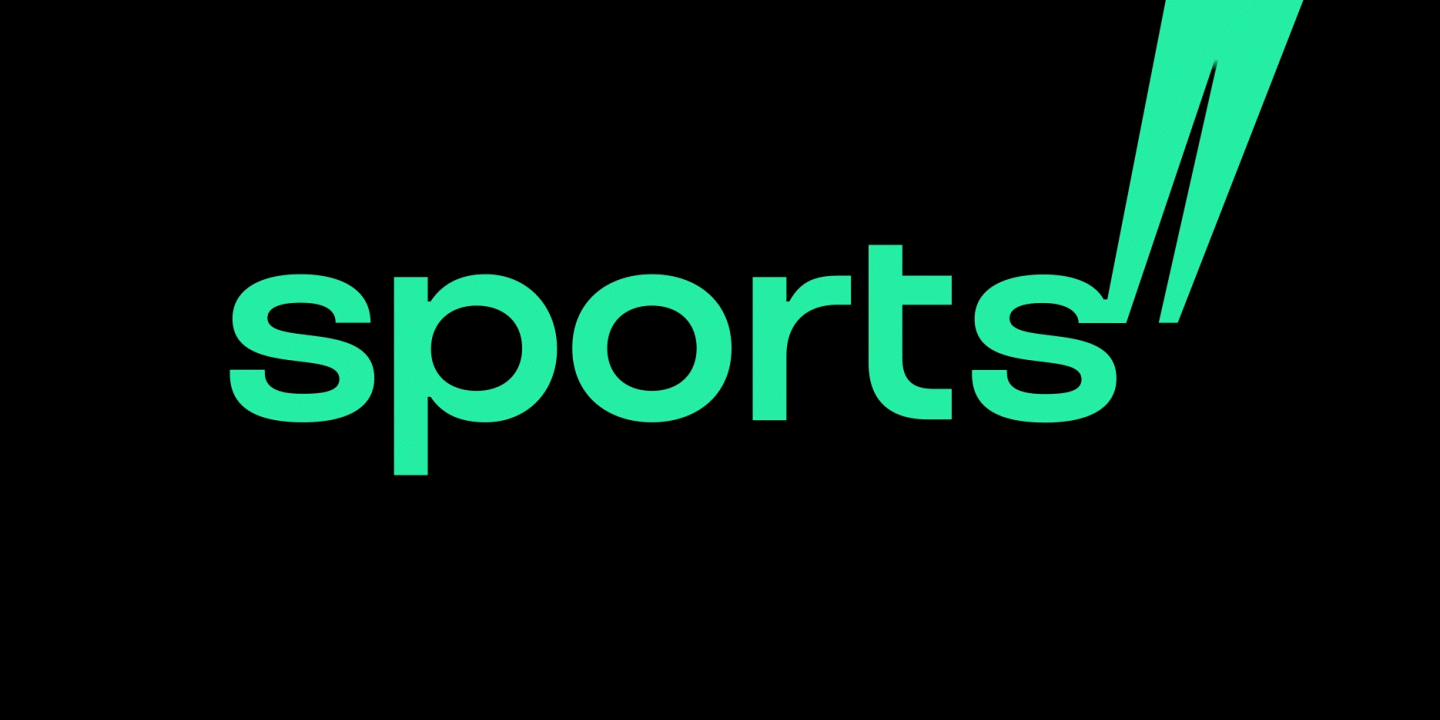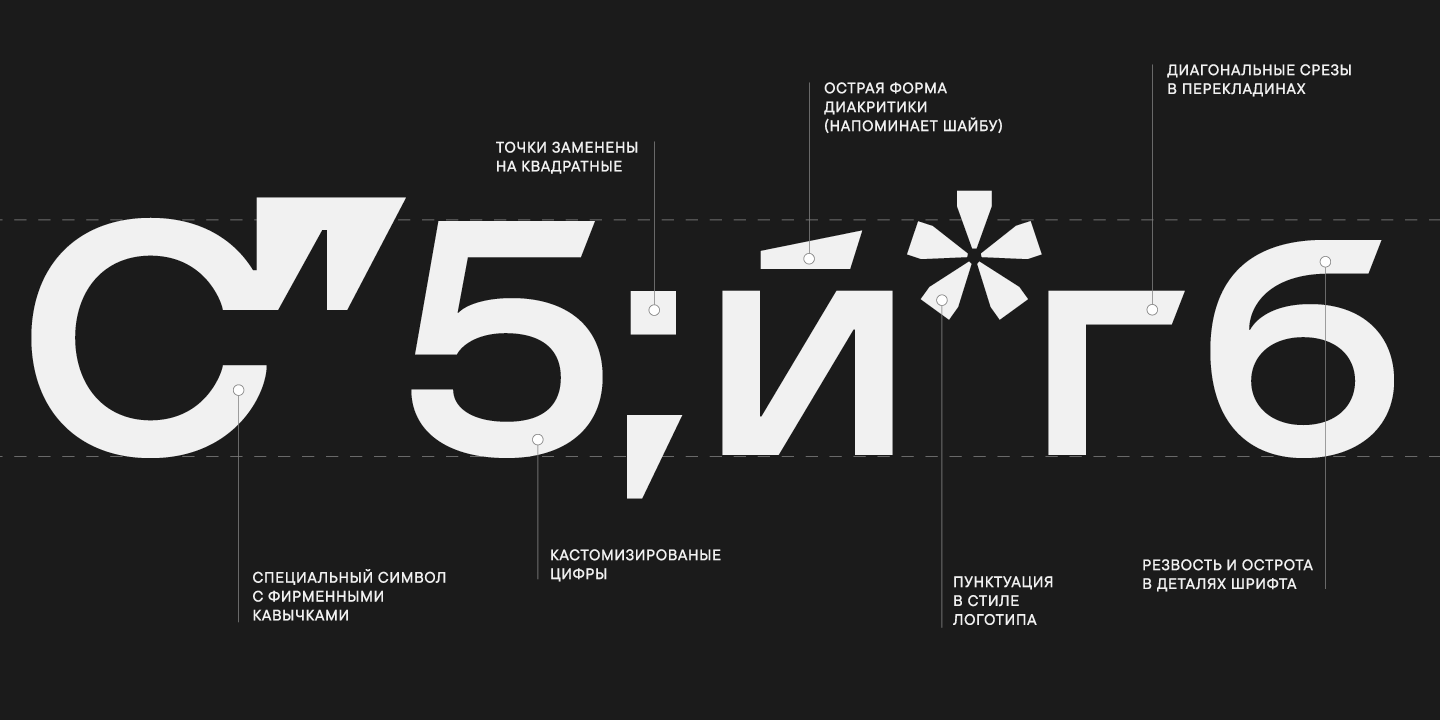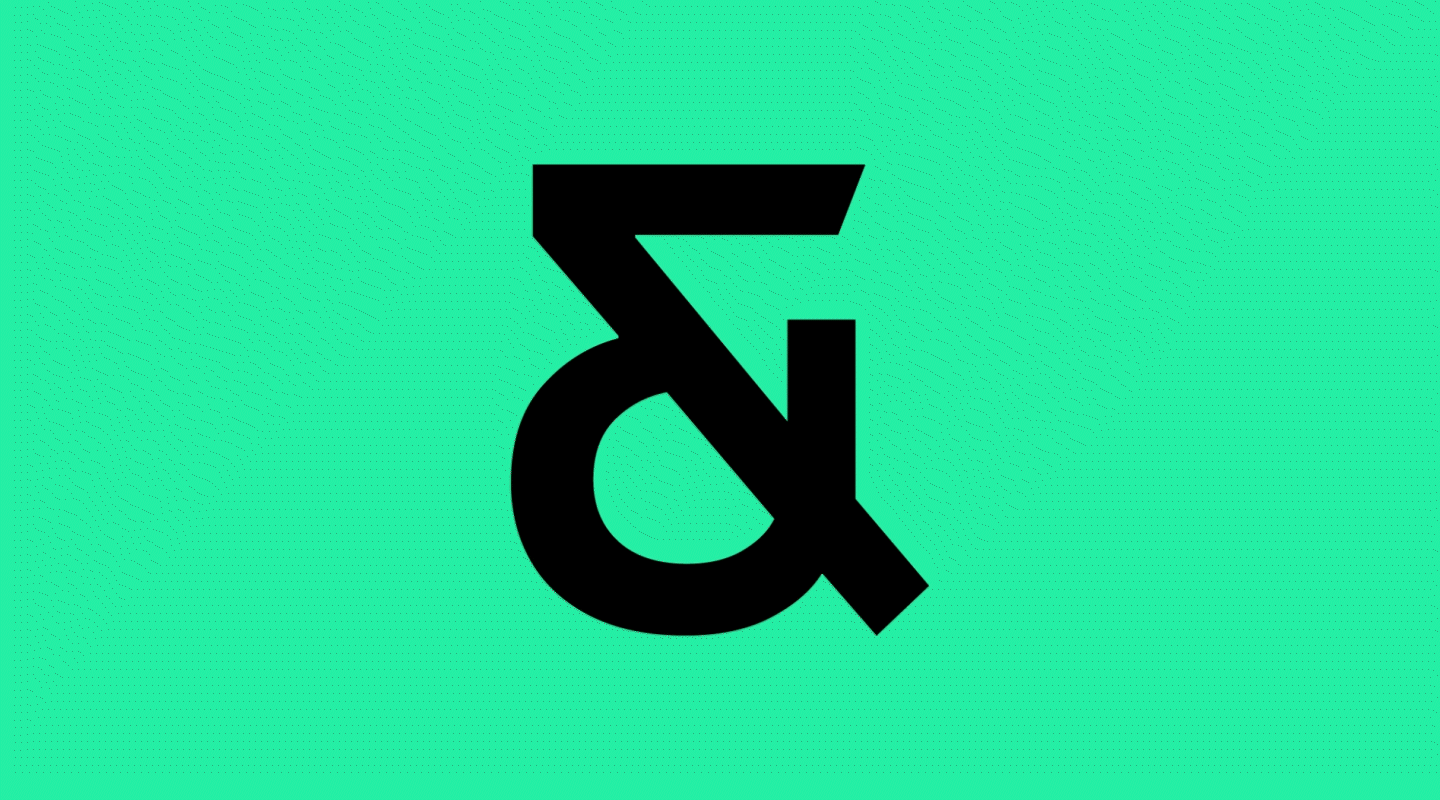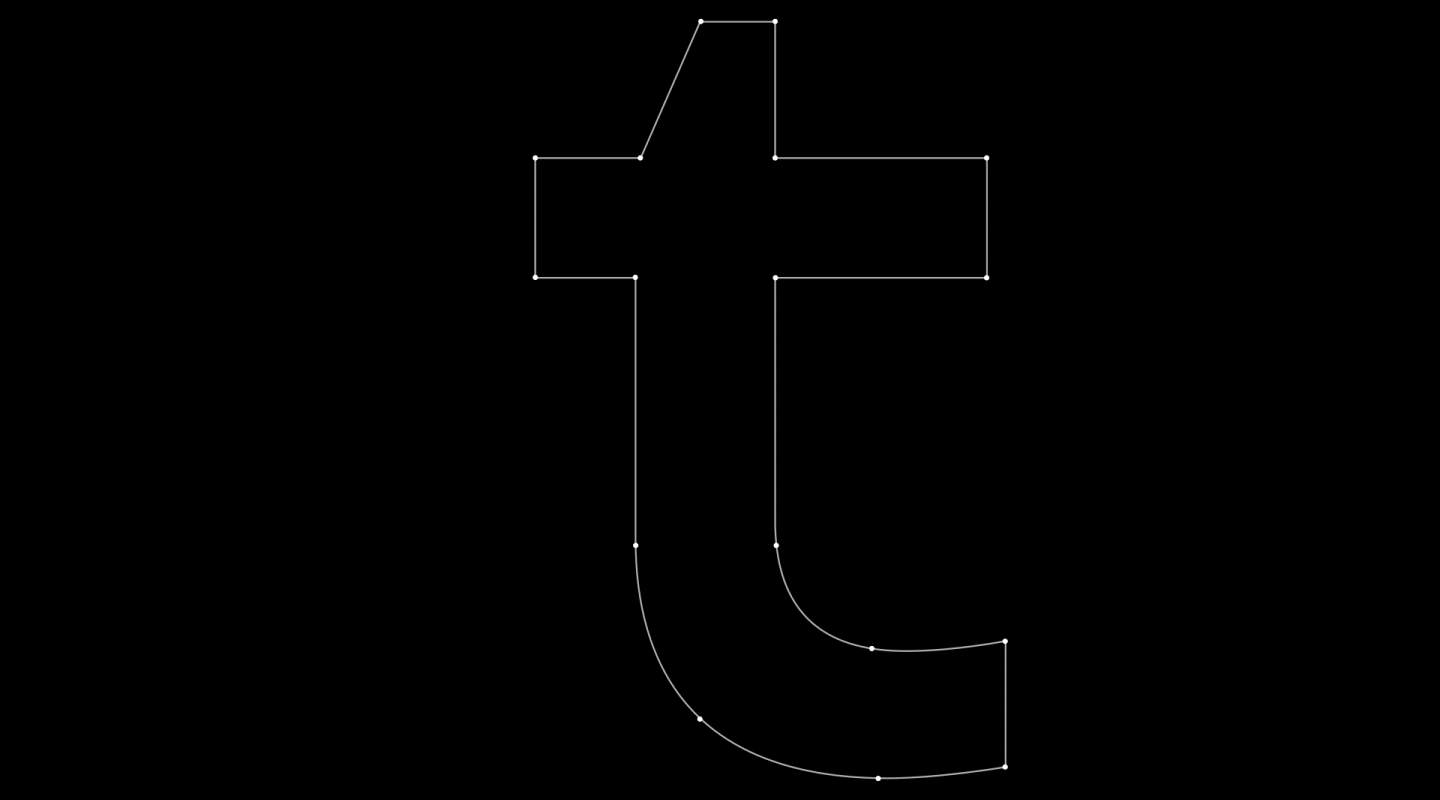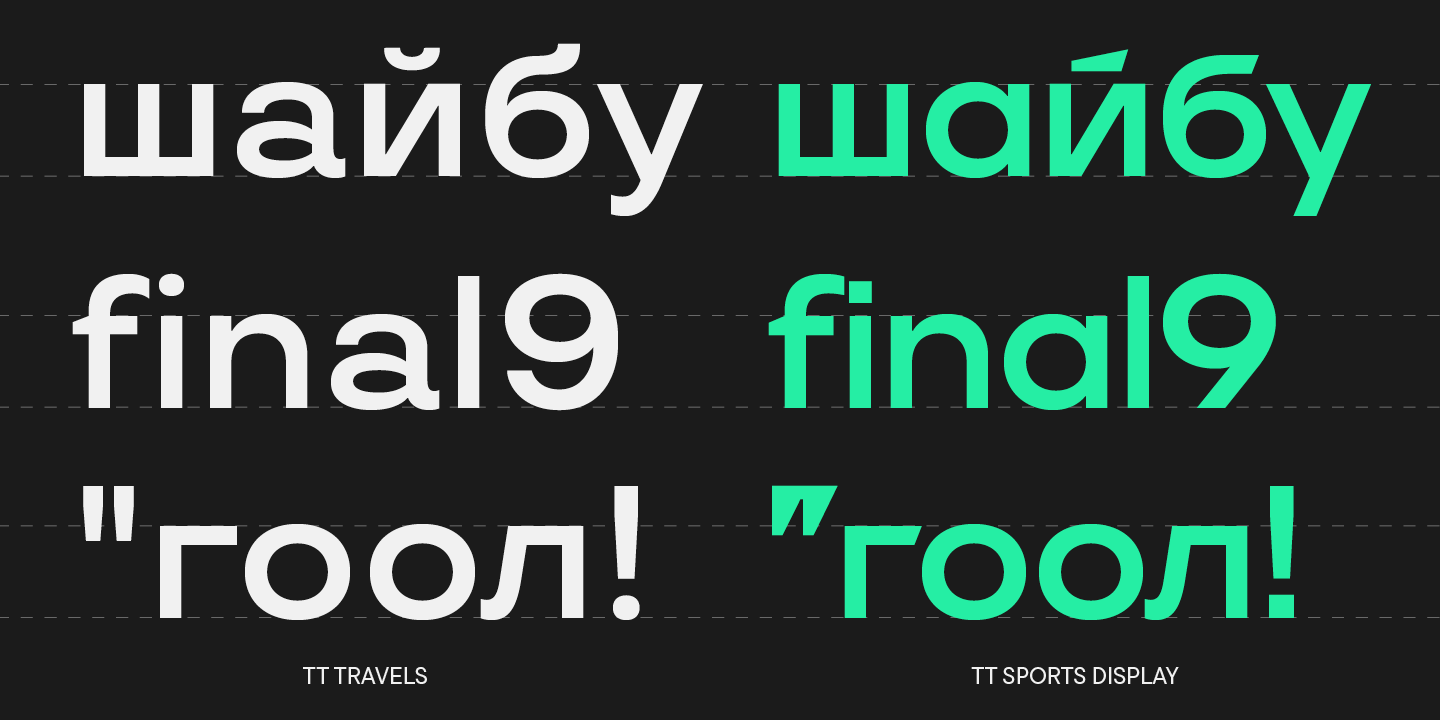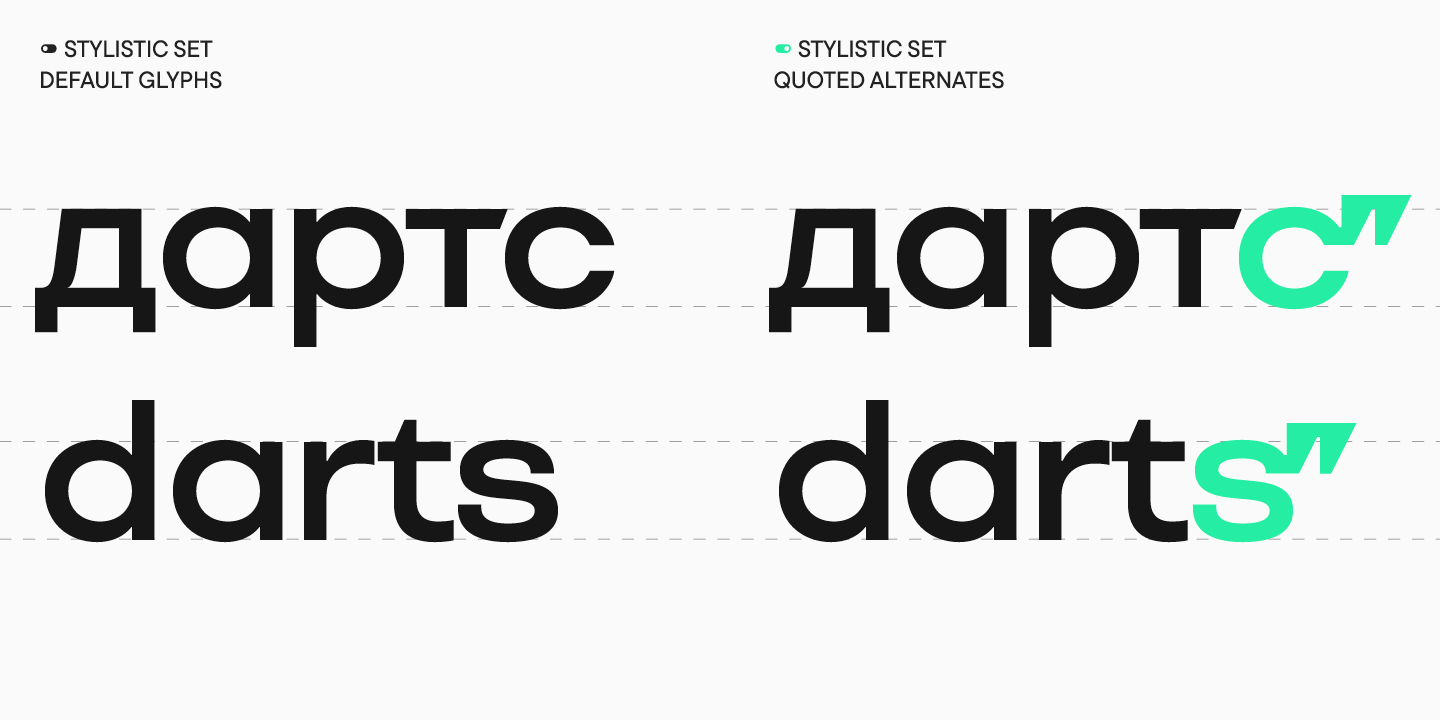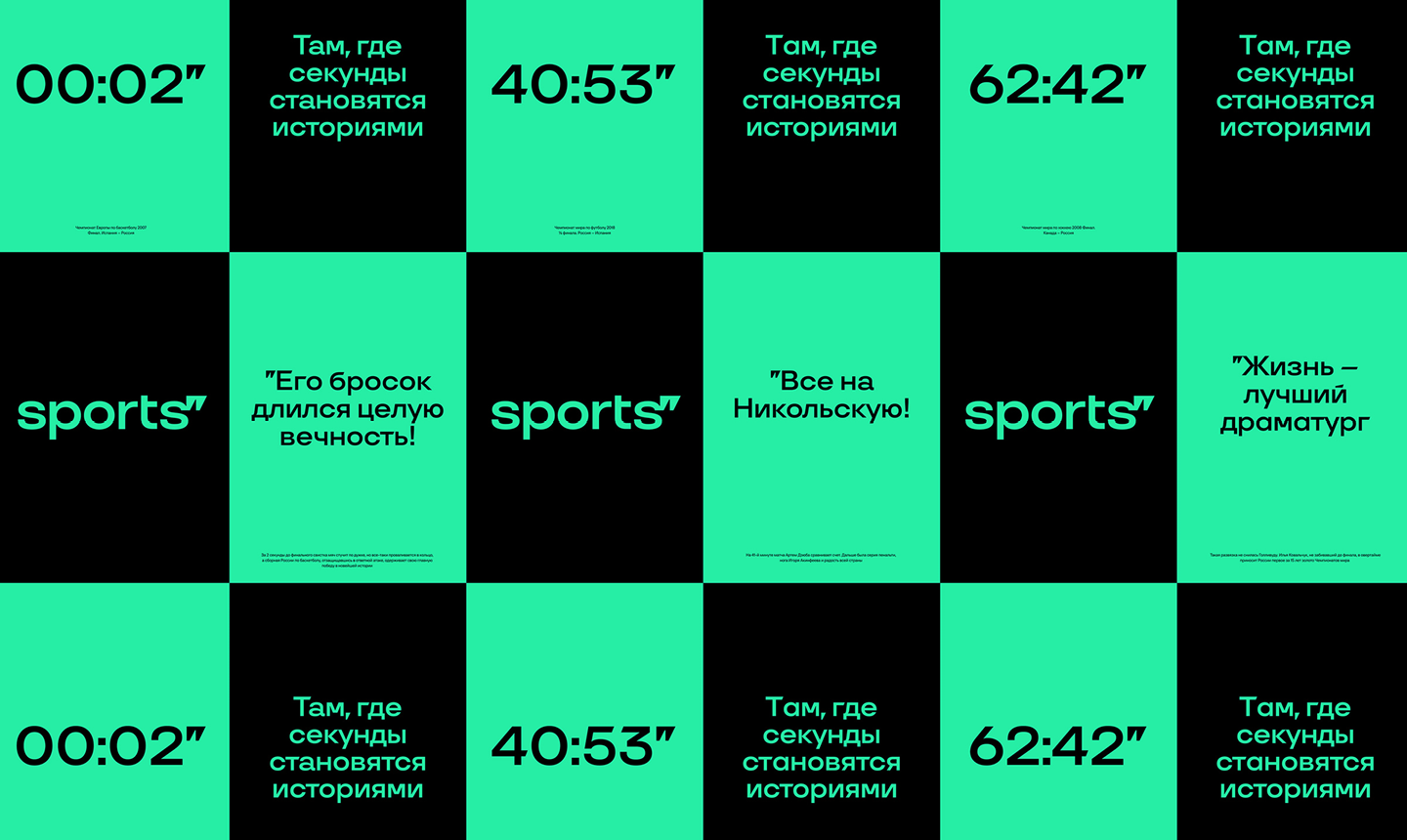
Кавычки и секунды: как мы создавали фирменный шрифт для Sports.ru
Издание Sports.ru провело масштабный ребрендинг — впервые за 18 лет компания изменила логотип, а также выбрала фирменный цвет. А еще у бренда появился собственный фирменный шрифт TT Sports Display от студии TypeType. Рассказываем подробности!
Предыстория: ребрендинг Sports.ru
Визуальный образ Sports.ru не менялся с 2006 года. За это время логотип с пятью разноцветными шариками перестал быть актуальным и отражать ценности бренда. Кроме того, компания расширяется и строит новые планы — ребрендинг стал символом этих перемен. Им занималось агентство «Супрематика», а в создании бренд-платформы приняло участие стратегическое агентство Relevant.
Так, от наименования бренда «отрезали» часть доменного имени «.ru»: теперь он называется просто Sports или «Спортс». Такое сокращение не только сделало форму более лаконичной и простой для произношения, но и помогло подчеркнуть, что современный Sports — это не только сайт, но также линейка приложений и семейство пабликов в соцсетях.
Опорной точкой всего концепта стал новый логотип компании, дополненный «кавычками-секундами» — то есть кавычками, форма которых отсылает к международно признанному знаку секунд на секундомерах и табло. «Супрематика» разработала логотип на основе нашего шрифта TT Travels, который мы позже кастомизировали для «Спортс» — об этом мы подробно расскажем во второй части.
«Sports — не просто цифровая платформа о спортивных событиях, но и сообщество блогеров, комментаторов и преданных своему делу сотрудников. И в спорте, и в журналистике каждая секунда на счету. Поэтому мы решили соединить два основных преимущества бренда в одном символе — так появились „секунды-кавычки“. А неразрывное сочетание знака с буквой „s“ отражает концепцию сильного сообщества, которым дорожит Sports».
Ксения Александрова, арт-директор «Супрематики»
Также у бренда появился фирменный цвет под названием Sports Green. Оттенок зеленого выбрали неслучайно: во-первых, отдали дань старому логотипу, сделав отсылку к одному из пяти цветных кругов. Во-вторых, зеленый символизирует обновление и напоминает цвет футбольного поля. А мятный оттенок добавил этим ассоциациям свежести и актуальности.
Всем этим изменениям предшествовало создание бренд-платформы, в рамках которой «Спортс» определил свою идентичность, характер, цели и ценности.
«В каждом элементе фирменного стиля мы стремились передать ощущение динамики, чтобы подчеркнуть обновленный характер Sports. Выбор главного цвета оказался непростой задачей — важно было не только сохранить связь с миром спорта и отстроиться от конкурентов, но и отразить эволюцию и диджитальность бренда».
Ксения Александрова, арт-директор «Супрематики»
Теперь предстояло актуализировать еще одну важную деталь фирменного стиля — шрифт. Он должен был отразить новые смыслы, задачи и идеи компании.
Как мы создавали фирменный шрифт для Sports
Итак, нам необходимо было сделать фирменный шрифт, который стал бы узнаваемым лицом бренда, и добавить ему уникальные фишки — но соблюсти меру, чтобы не перегрузить. При этом было необходимо, чтобы шрифт рифмовался с новым логотипом и гармонично вписывался в новый визуальный образ бренда. Как мы уже упомянули выше, решением стала кастомизация TT Travels — шрифта из коллекции TypeType.
Для начала мы провели аудит нового шрифтового логотипа, разработанного «Супрематикой», и предложили свои правки. После этого мы начали думать, как кастомизировать TT Travels так, чтобы шрифт получился уникальным и вмещал в себя элементы фирменного стиля.
Первой идеей для развития шрифта было создать два заголовочных сета, в которых к каждой букве с двух сторон были бы прикреплены те самые «секунды», чтобы заголовки рифмовались с логотипом. Также «Спортс» хотели отойти от классических представлений о шрифте со «спортивной тематикой», то есть аутлайны (контурные шрифты) и брусковые засечки сразу отпадали.
Нам было важно не просто изменить отдельные символы, а сделать так, чтобы кастомизированный шрифт стал узнаваемым, отражал характер бренда. Мы стремились добавить резвости и динамичности в разные элементы знаков: например, диакритику и пламевидный элемент буквы «б». А еще мы решили поработать с пунктуацией и сделать цифры более узнаваемыми, так как они часто используются в текстах на тему спорта.
Мы собрали мудборд, чтобы определить, в какую сторону двигаться дальше. В качестве одного из вариантов развития проекта предложили добавить более акцидентные цифры, отражающие спортивную тематику. Например, сквадраченные формы как на спортивных табло или полигональные, как на форме.
В результате мы решили сделать цифры в той же стилистике, что и весь шрифт, а динамику подчеркнуть другим способом — с помощью скосов в терминалах.
Над проектом работали: